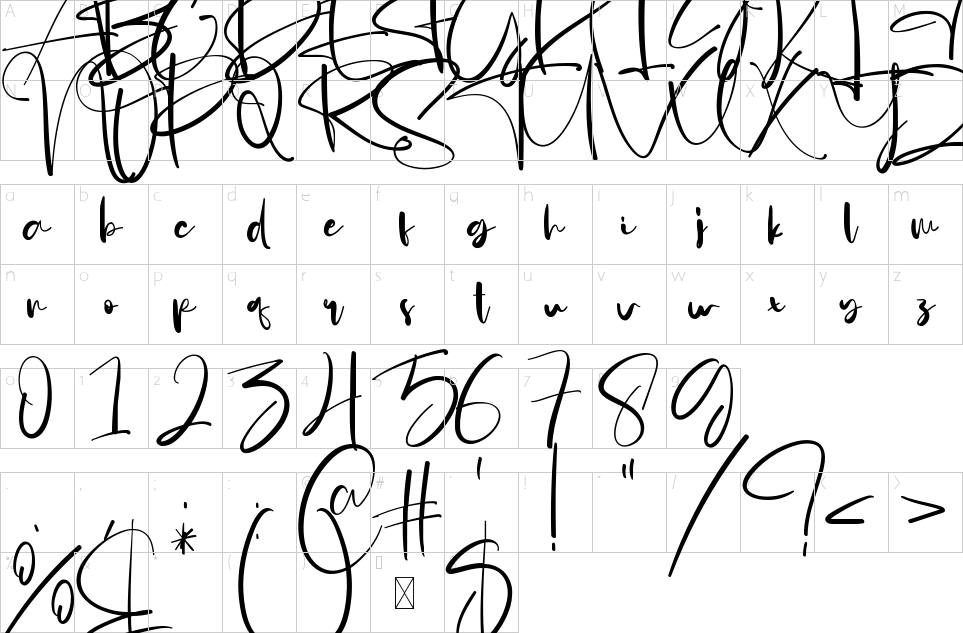
Descubra a elegância e a versatilidade da Animate Font, uma fonte grátis projetada para Windows e Mac. Desenvolvida por scratchones, esta fonte possui um design arrojado que se destaca em qualquer projeto gráfico. Através de sua natureza fluida e animada, ela pode transformar textos em uma obra de arte. Com uma alta popularidade, já foi baixada 535 vezes, demonstrando a sua qualidade e versatilidade. Seja você um profissional de design ou um iniciante, Animate Font é uma opção ideal para adicionar um toque único e moderno aos seus trabalhos. Baixe já e experimente a diferença que ela pode fazer para seus projetos.